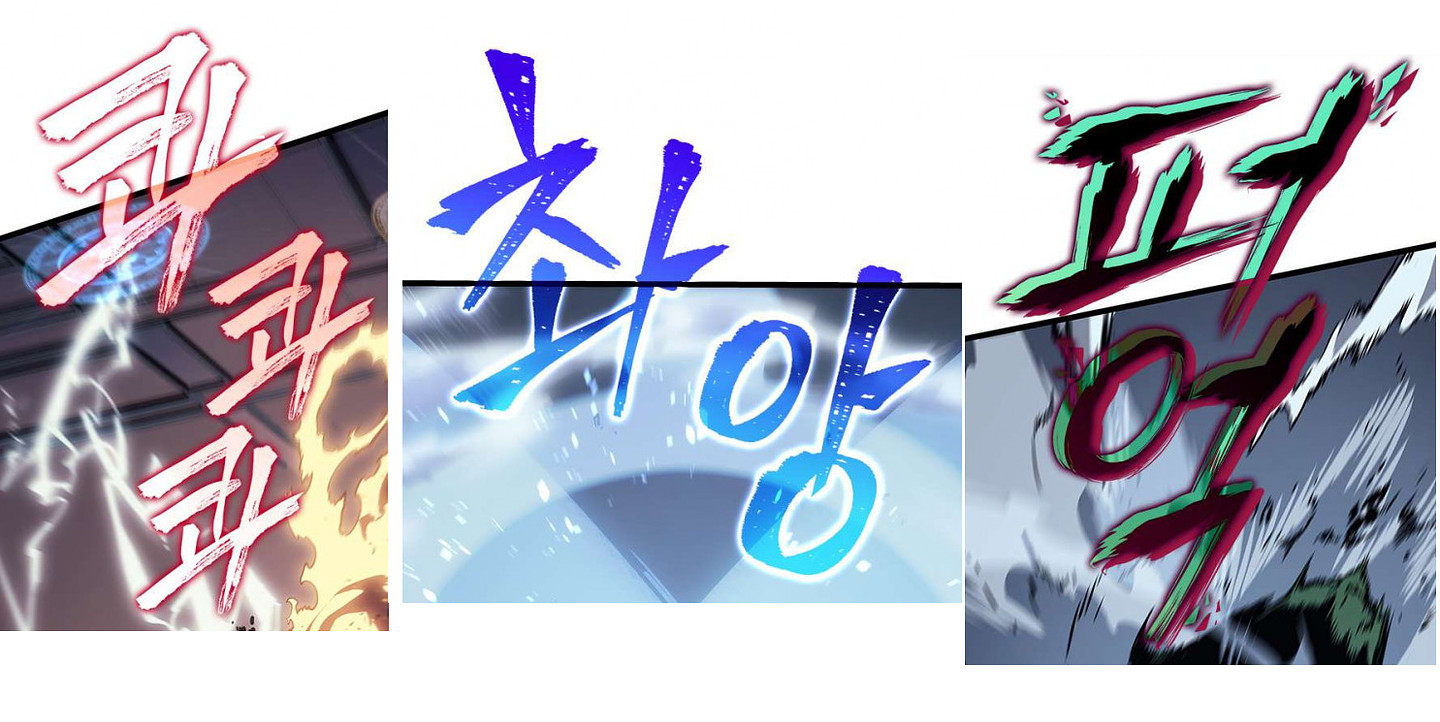
웹툰 효과음 폰트인데... 어느정도 보정이 들어간건 알겠지만 기본 베이스로 되는 폰트가 어떤건지 궁금합니다! ㅜㅜ
두번째의 경우 다음 클립스튜디오 브러쉬를 이용해 직접 쓴거 같구요. https://assets.clip-studio.com/ko-kr/detail?id=1686820 첫번째와 세번째도 아마 직접쓰지 않았을까 싶습니다.